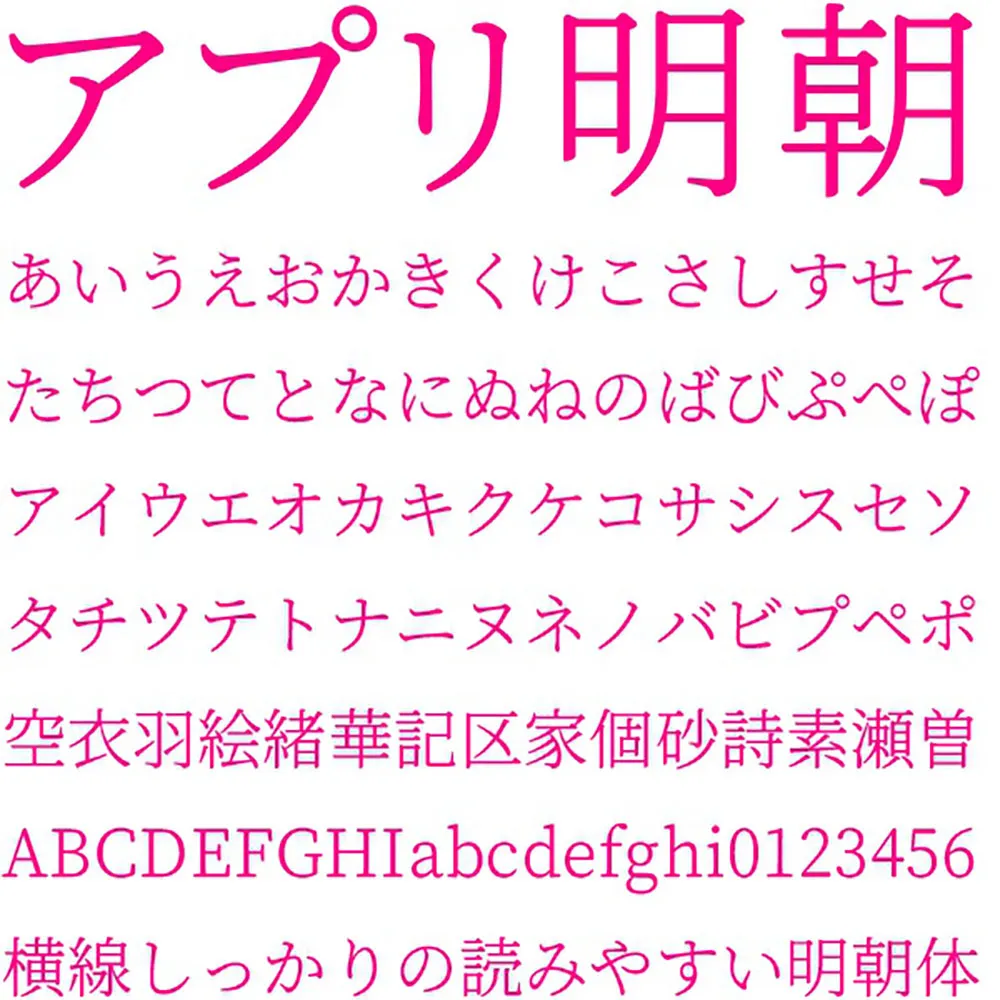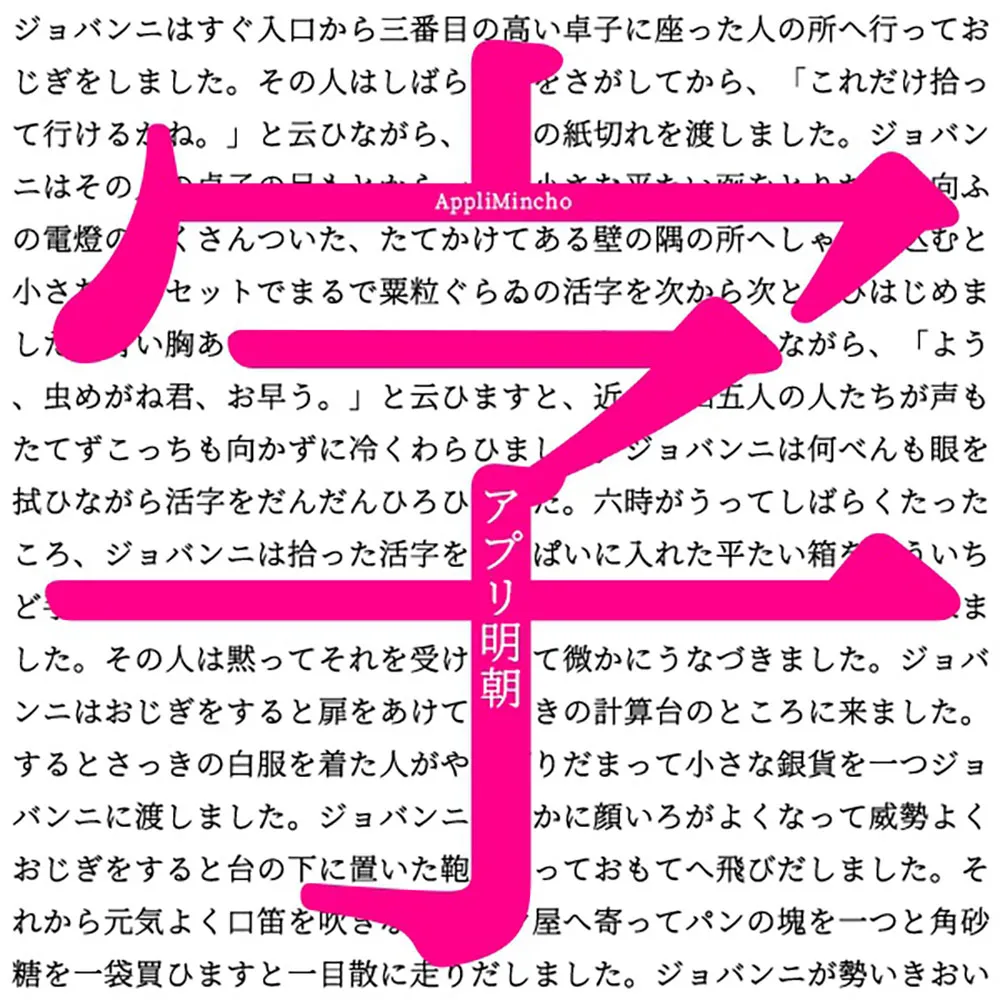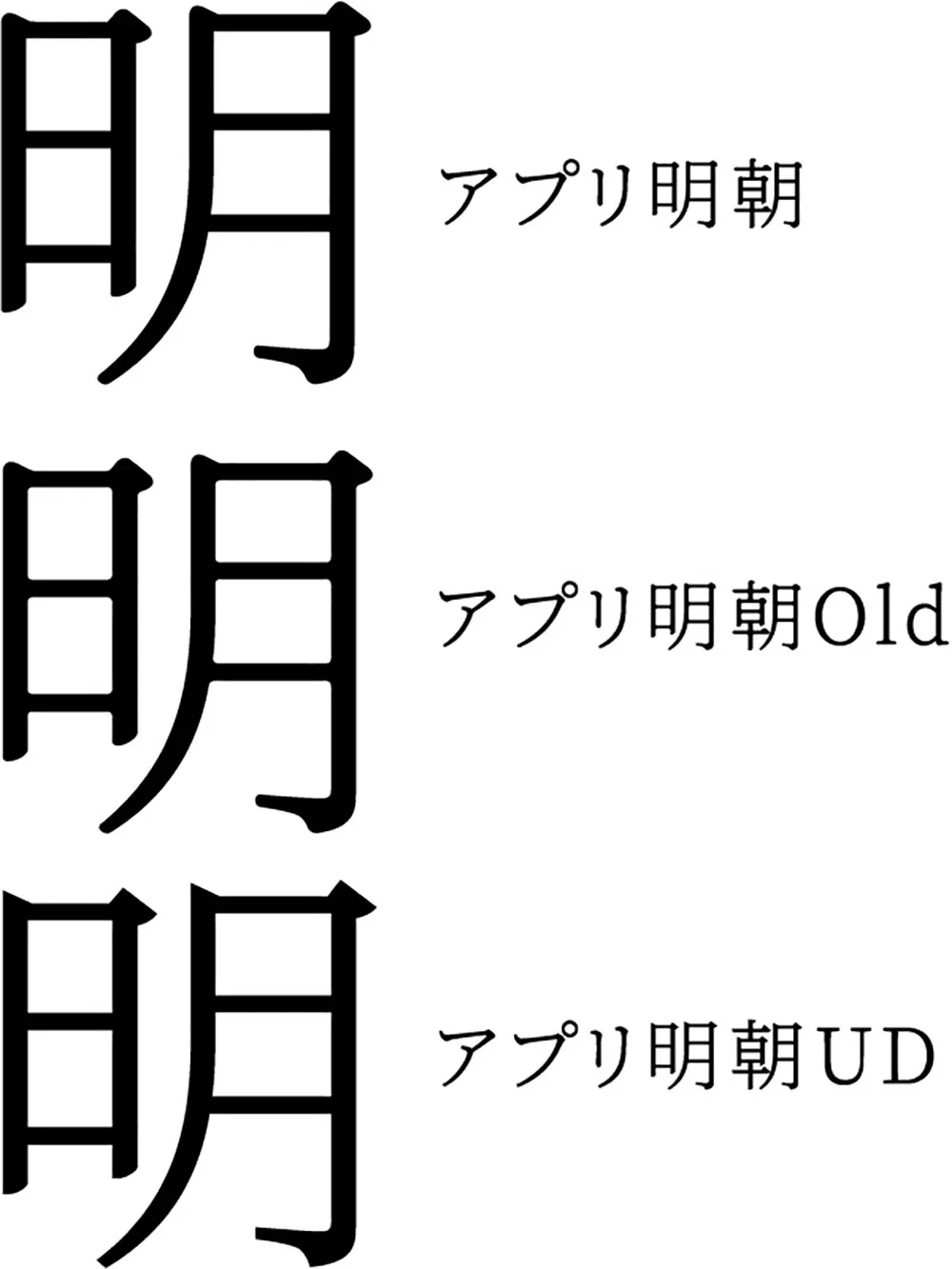
アプリ明朝是一款利用思源宋體的精彩之處的橫線稍微粗一點的橫太明朝體。與思源宋體相比,橫線稍粗,縱線稍細。另外,鱗片、停頓等都更加圓潤,不會妨礙視線移動,有助於漢字的自然設計和易讀性,具有柔和的氛圍,與平假名等形成整體的統一感。
除了アプリ明朝以外,還附帶兩種字體,在文字上加入滲透,再現墨塊的老風味的 “ アプリ明朝Old ” ,鱗片處理銳利的簡單的 “ アプリ明朝UD ”。
源ノ明朝の素晴らしさを活かした橫線が少し太い橫太明朝體です。源ノ明朝と比べると、橫線が少し太く、縦線が少し細くなっています。またウロコ、止め等が丸くなって、目の動きの邪魔にならず漢字の自然なデザイン・読みやすさに繋がっていますやわらかい雰囲気で、ひらがな等との全體の統一感があります。
アプリ明朝以外にも2つのフォントを同梱しています。文字に滲みを加え墨だまりを再現したオールド風味の「アプリ明朝Old」ウロコの処理がシャープなままのシンプルな「アプリ明朝UD」